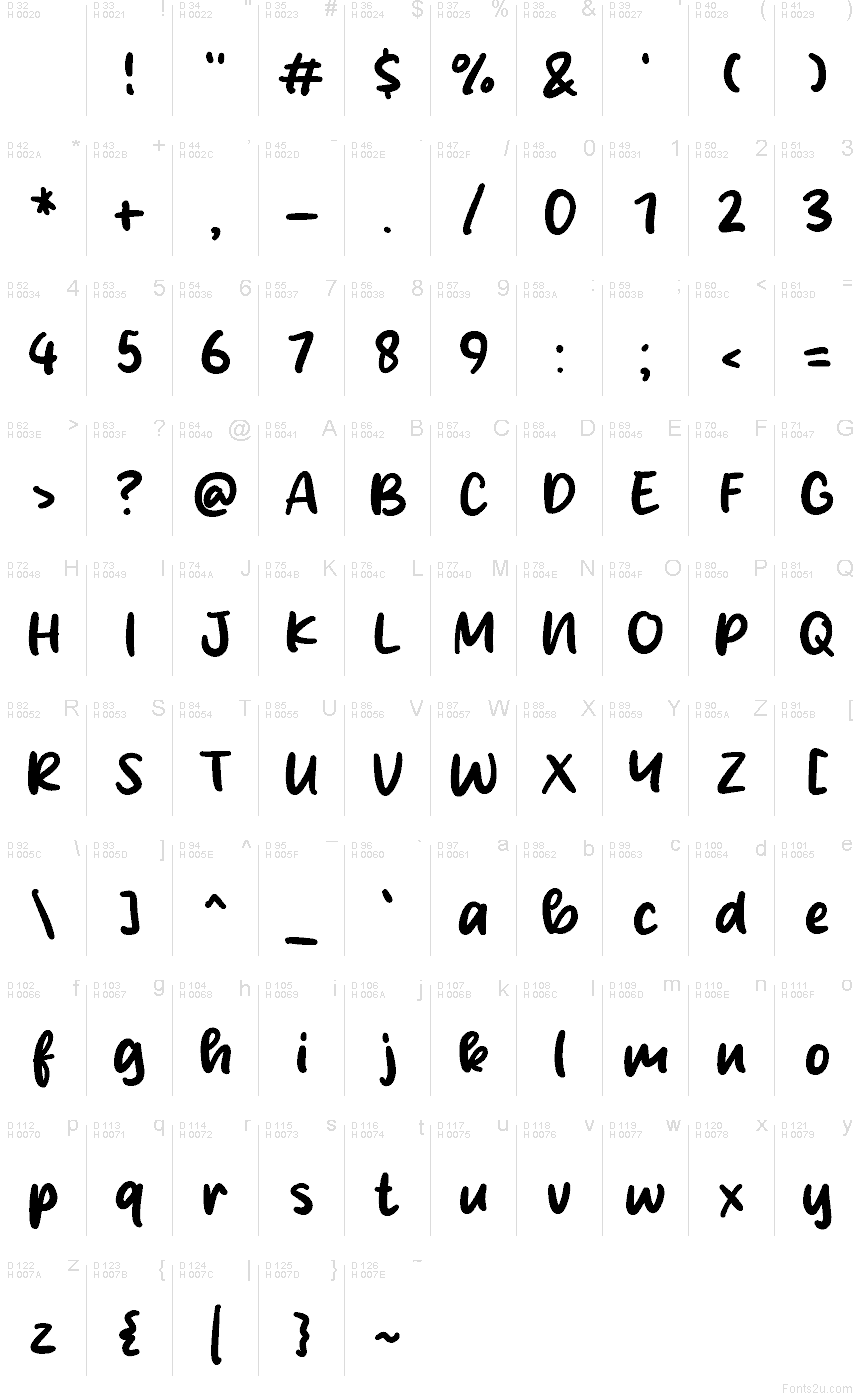
Milk Yogurt od Milk Yogurt to darmowy, odręczny font pędzlowy o swobodnym, nowoczesnym charakterze. Litery opierają się na grubych, zaokrąglonych pociągnięciach i szybkich łączeniach, co nadaje im luźną dynamikę pisma markerem, zamiast sztywnej kaligrafii.
Idealnie pasuje do brandingu kawiarni i marek kosmetycznych, nagłówków plakatów, wpisów w mediach społecznościowych, opakowań oraz krótkich tekstów, gdzie potrzebny jest darmowy font z przyjaznym, nieformalnym wydźwiękiem. Użyj go, gdy chcesz, aby słowa sprawiały wrażenie napisanych pewnym ruchem, z wystarczającą masą i dynamiką, by stanowić podstawę dla logo, plansz tytułowych czy dużych cytatów.